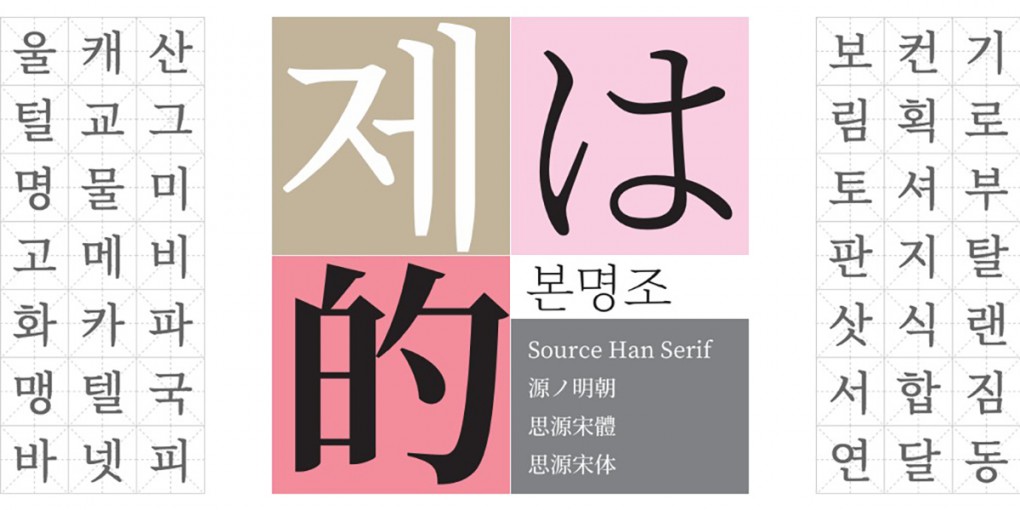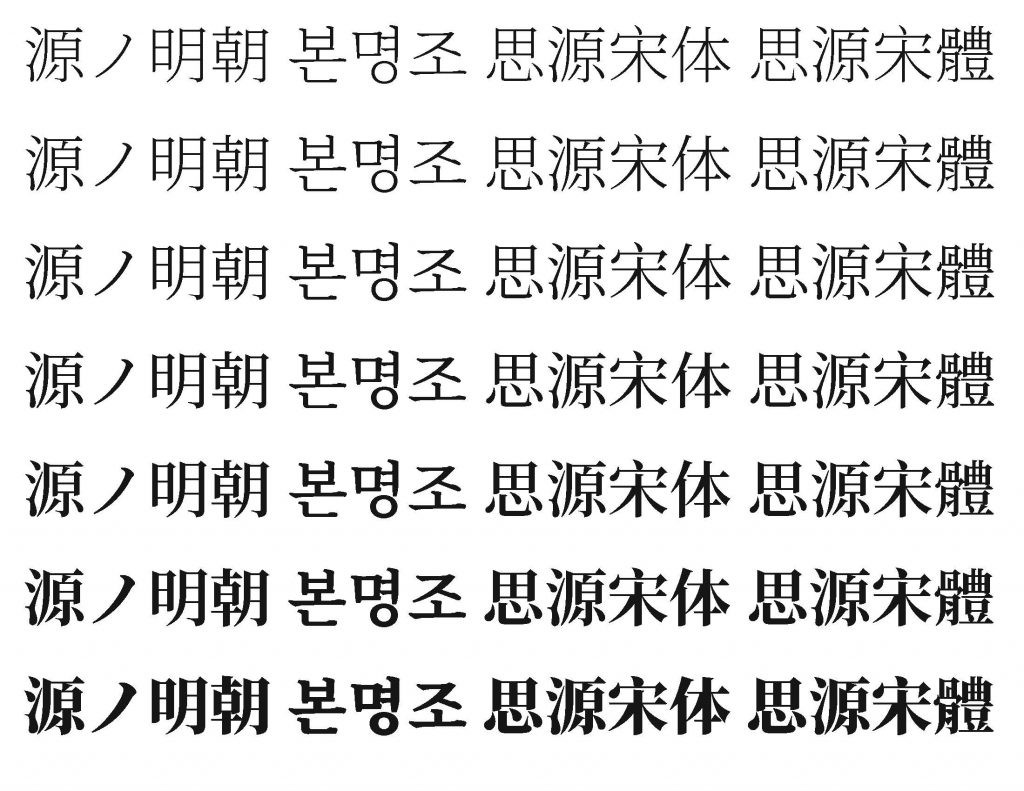
어도비, 구글 그리고 산돌 = ‘본명조’ 탄생!
어도비가 동아시아 15억 명 사용자의 디자인 통합 요구를 반영한 새로운 오픈소스 서체 ‘본명조’를 발표했다.
어도비, 구글 그리고 산돌 = ‘본명조’ 탄생!
어도비가 한국어를 비롯, 중국어, 일본어를 동시에 지원하는 본명조(Source Han Serif)를 발표했다. 이는 동아시아 15억 명 사용자의 디자인적 통합 요구를 반영하여 오픈소스 서체를 제작 및 배포한 것이다. 본명조는 화면 디스플레이에 최적화되어 있는 것은 물론, 문학 작품에 사용되는 텍스트나 우아하고 세련된 제목에 잘 어울리며 특히 인쇄 시에 수려함이 돋보인다고 어도비 관계자는 밝혔다.
“다양한 최신 디바이스에서 모든 언어를 표현하는 고품질의 조화로운 글꼴 모음을 개발한다는 이 글꼴 프로젝트의 목표는 규모와 범위 면에서 벅찬 과제였다. 한중일 언어는 10억 명 이상의 사용자에게 너무나 절대적이다. 디지털 타이포그래피의 선구자인 어도비는 수려한 한중일 언어를 개발하는 데 완벽한 파트너이다” – 밥 정, 구글 국제화 부문 책임자
지난 2014년 발표된 ‘본고딕(Source Han Sans)’의 자매 서체로써 개발된 본명조는 단일 서체 모음 안에서 한국어, 중국어 간체, 중국어 번체, 일본어 등 4개의 동아시아 언어와 더불어 라틴어, 그리스어 및 키릴 등 서양 언어권 글리프도 제공한다. 또한, 서체 당 7가지 웨이트로 표현되는 65,535개 글리프가 제공된다. 한국어의 경우, 자주 사용되는 한글 음절 및 결합된 자모와 함께 모든 현대 기호, 문자 및 음절을 지원한다. 따라서, 디자이너와 컨텐츠 제작 개발자들은 언어에 상관없이 단일 서체를 사용할 수 있게 됨에 따라 언어별로 사용 가능한 서체를 찾아야 하는 불편이 없어진다.
어도비와 구글의 협업을 통해 진행된 이 서체 개발 작업에는 산돌커뮤니케이션을 비롯하여, 일본의 이와타(Iwata), 중국의 창저우 시노타입(Changzhou SinoType) 등 한중일을 대표하는 폰트 디자인 기업들이 참가했다. 구글은 본명조를 구글의 노토 범 유니코드(Pan-Unicode) 서체 모음 중 하나인 노토 세리프 CJK(Noto Serif CJK)라는 이름으로 제공할 예정이며, 현재는 어도비 타입킷과 오픈소스 공유 웹사이트 깃허브(GitHub)를 통해 모든 사용자에게 무료로 제공된다. 이와 더불어 산돌구름 서비스에서도 공개폰트로 업데이트되어 누구나 무료로 사용이 가능하다.